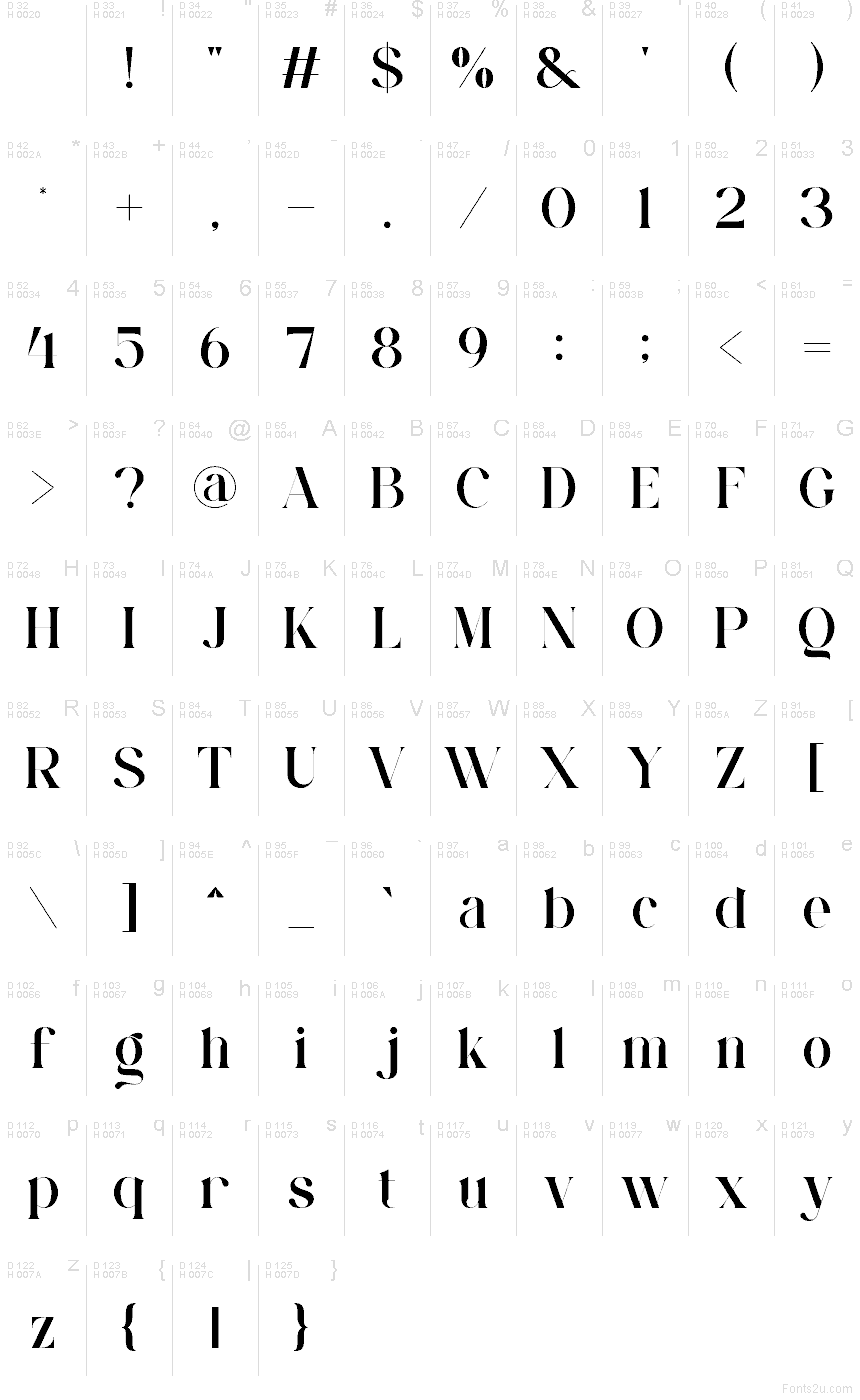
Vakonie Regular
Vakonie od ErmediaStudio je bezplatné písmo so serifmi, ktoré vyzerá, akoby bolo vyrezané nožom a nie kreslené perom. Vysoké, elegantné písmená sú pretínané výraznými, sýtymi ťahmi, čo dodáva celému tvaru sošný, takmer filmový nádych. Ostré diagonály a tesné krivky vytvárajú dojem pohybu aj v jedinom slove, vďaka čomu pôsobí Vakonie luxusne, dramaticky a zároveň trochu nekonvenčne.
S použitím Vakonie získajú nadpisy a logotypy silný, módny hlas, ktorý skvele funguje v brandingu, na obálkach časopisov, plagátoch, obaloch, lookbookoch a grafike pre sociálne siete. Tento bezplatný font vynikne pri použití vo veľkom formáte, kde môžu jeho výrazné rezy a plynulé krivky skutočne dýchať. Vakonie kombinujte s jednoduchým, čistým bezpätkovým písmom v hlavnom texte, aby zostalo rozvrhnutie vyvážené a čitateľné, pričom písmo so serifmi sa postará o vizuálne rozprávanie.